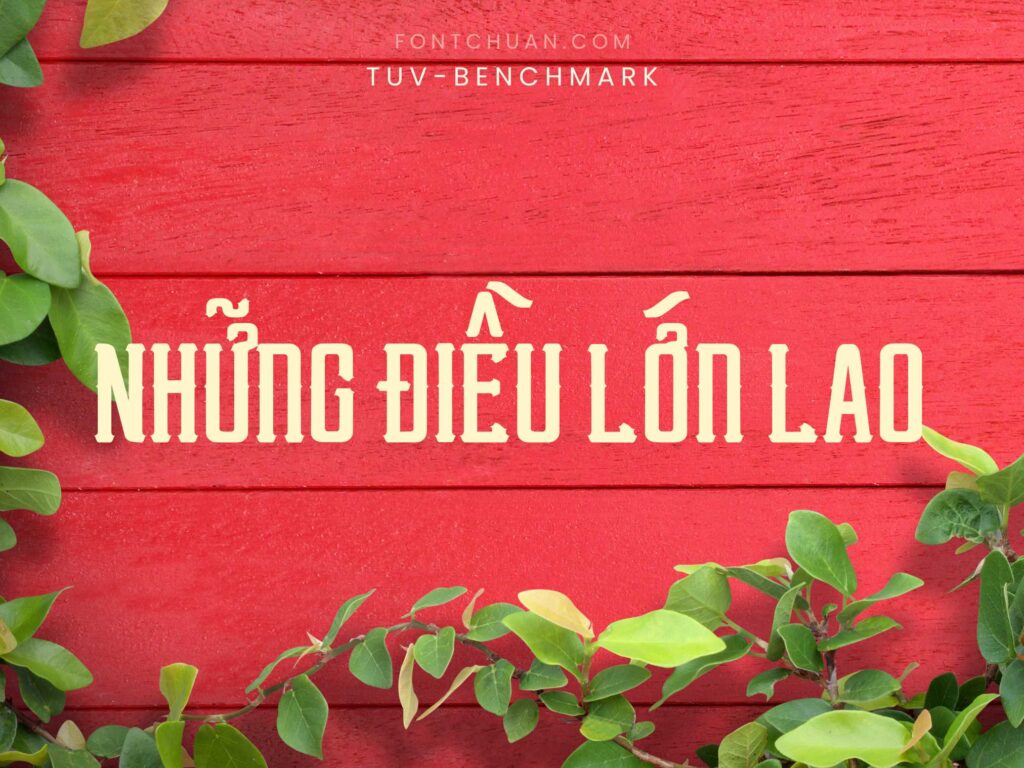
Font TUV Benchmark Việt Hóa
Tác giả Font: Alphabet Agency
Việt hóa bởi: Thùy Uyên
Benchmark là một font chữ hiển thị chất lượng cao, được thiết kế bởi Jon Swinn. Font này mang phong cách cổ điển, dễ dàng kết hợp với các thiết kế và kiểu chữ khác. Ban đầu, Benchmark được tạo ra để sử dụng trong các logo bóng chày, nhưng cũng hoạt động hiệu quả trong các chủ đề vintage và retro. Font đã được Việt hóa để hỗ trợ tiếng Việt bởi Thùy Uyên, giúp người dùng Việt Nam dễ dàng áp dụng trong các dự án thiết kế. Font này được sưu tầm và chia sẻ bởi thành viên của Font Chuẩn, đáp ứng nhu cầu sử dụng đa dạng trong cộng đồng thiết kế.
Đặc điểm thiết kế của Benchmark bao gồm các ký tự in hoa được cách điệu, tạo nên sự linh hoạt trong thiết kế. Font này phù hợp cho các ứng dụng như thiết kế tiêu đề, logo, thiệp mời và các dự án sáng tạo khác. Các ngành nghề phù hợp bao gồm quảng cáo, giáo dục và công nghệ.